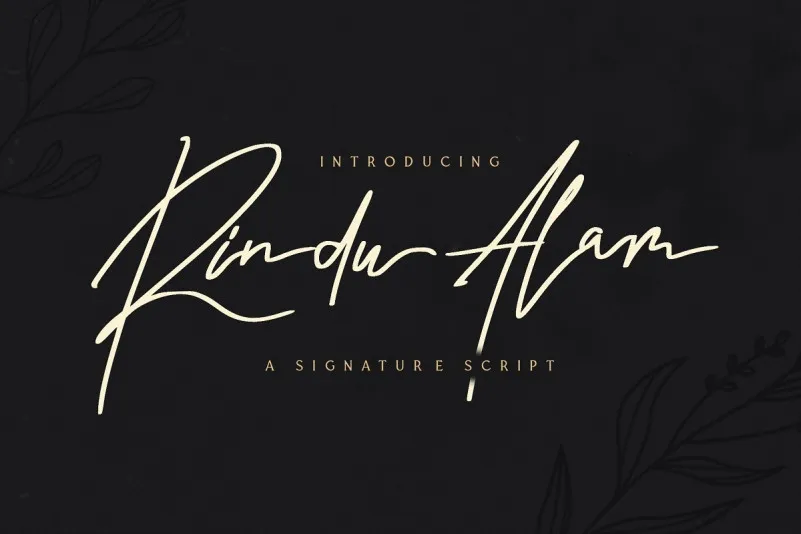
Rindu Alam Signature Font – Download Grátis
Descubra a beleza do Rindu Alam Signature Font no seu projeto! Esta elegante tipografia Script é perfeita para aquelas ideias modernas e sofisticadas. Se você está procurando uma fonte de assinatura simples e refinada, o Befonts pode ajudá-lo. O Rindu Alam Signature é perfeito para marcas fashionistas, convites de casamento, cartões de negócios, logotipos ou até mesmo como um belo elemento de calligrafia. Este arquivo fonte contém uma gama de estilos agradáveis e criativos que vão adicionar um toque único à sua criação. Para designers que buscam algo diferente e sofisticado, o Rindu Alam Signature é definitivamente a escolha certa para tornar seus projetos singulares e irresistivelmente elegantes.